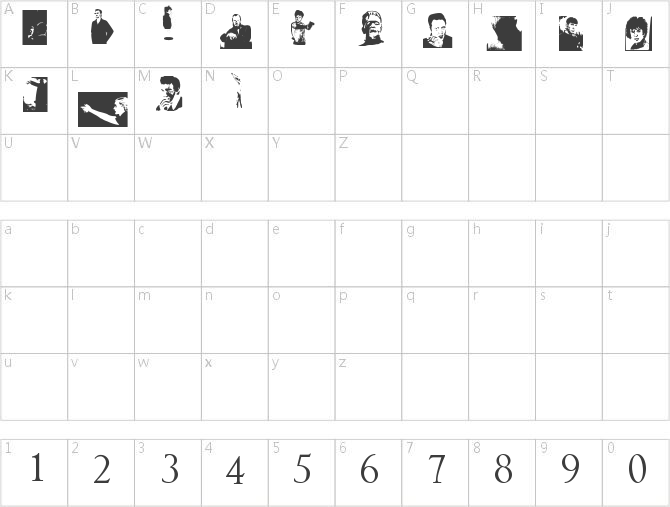
No-Perfect-People-Dingbats
No-Perfect-People-Dingbats介绍
No-Perfect-People-Dingbats字体字库是一款让人赏心悦目、百看不厌的英文字体,适合各类广告和产品包装设计应用,字体大小0.06MB,格式为ttf字体,上传用户是xqy,作者/版权方为未知